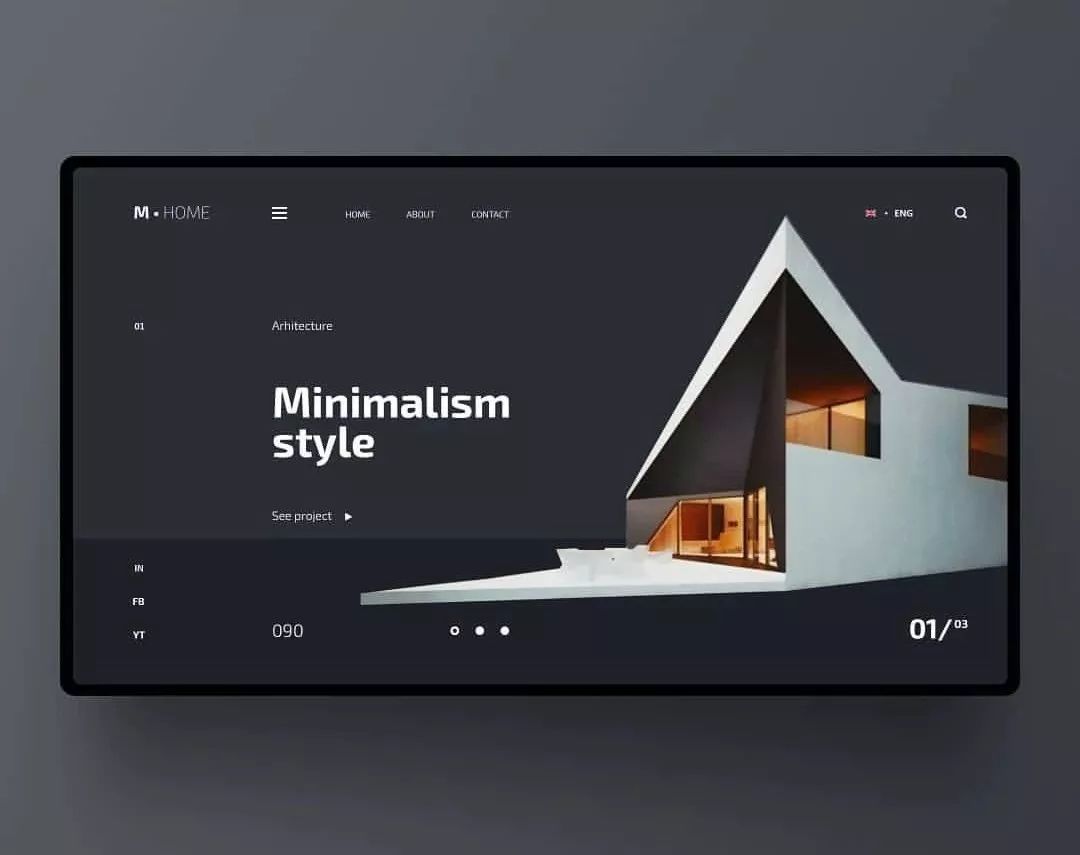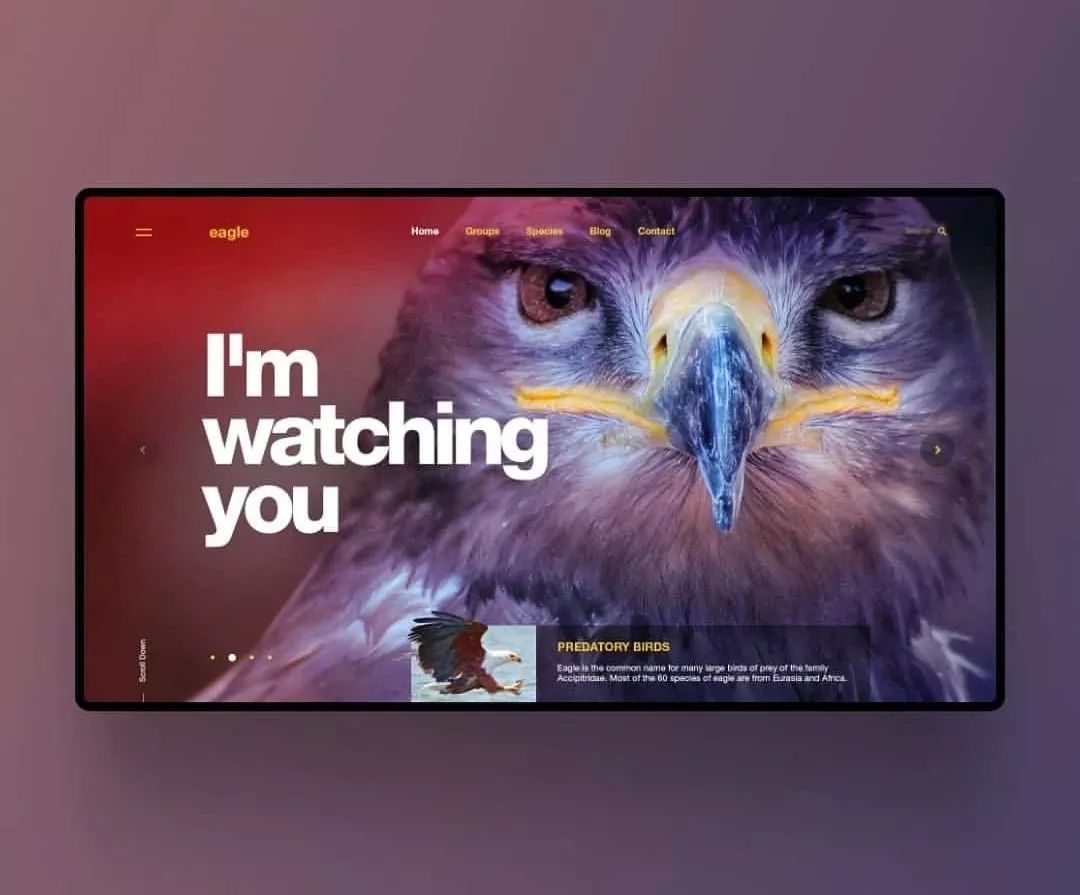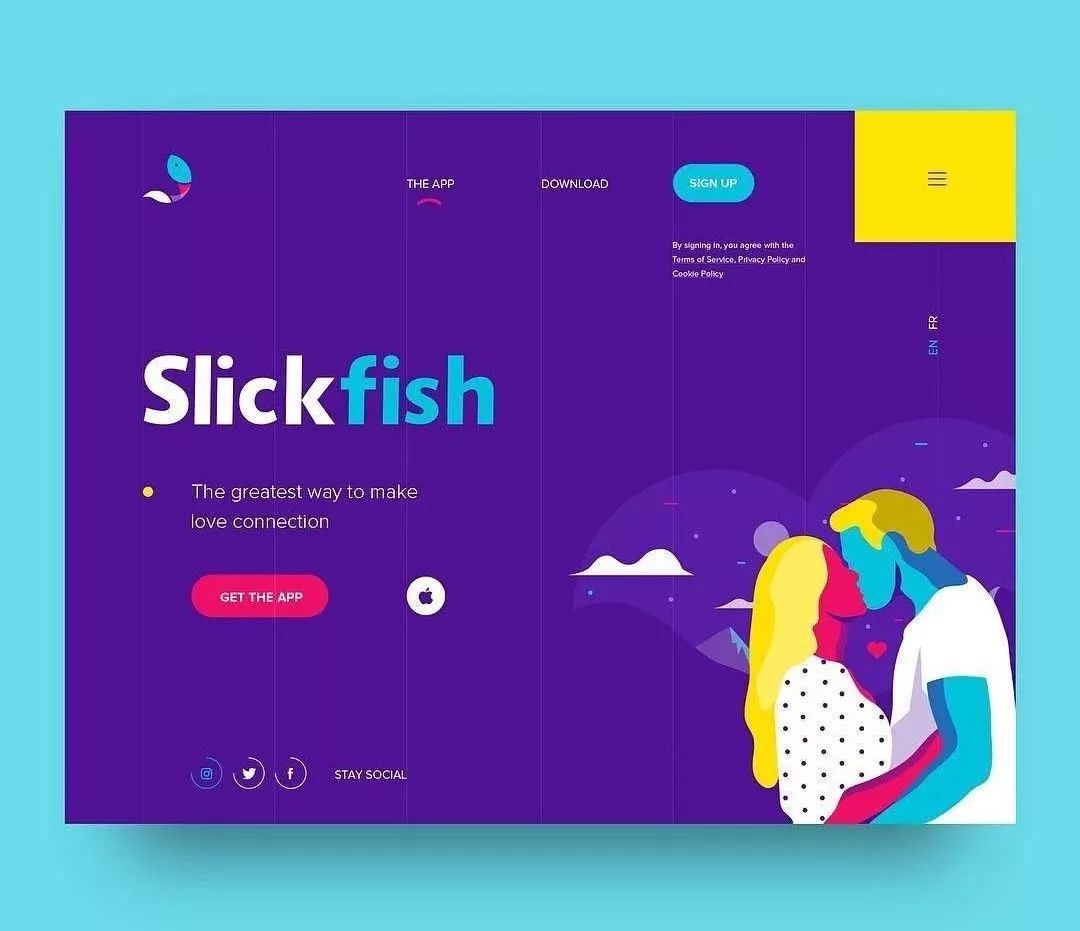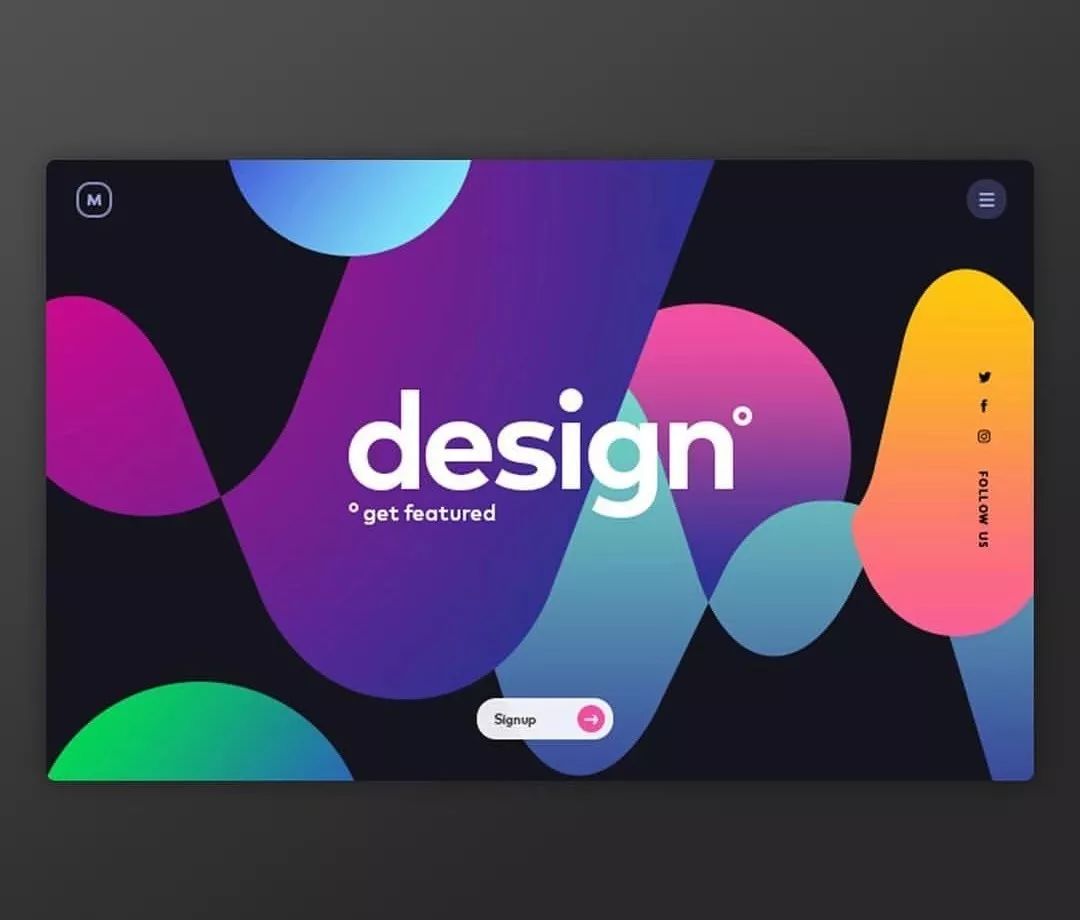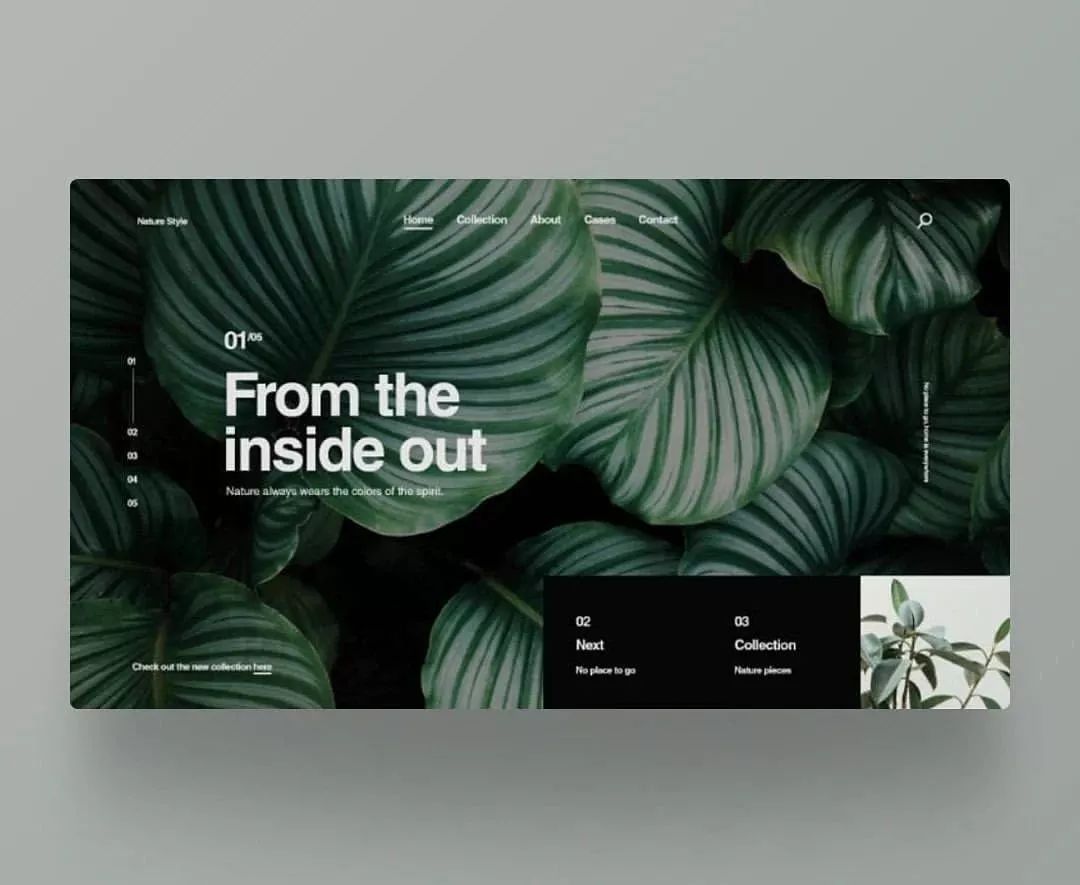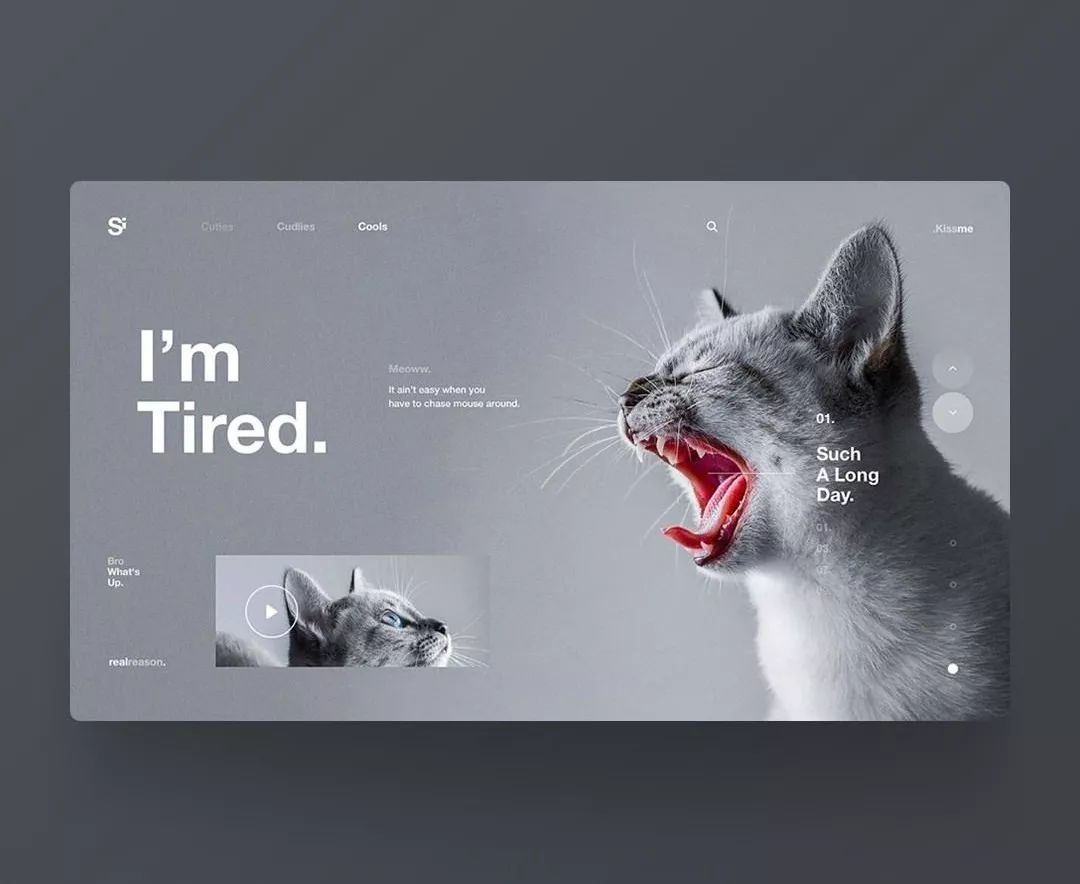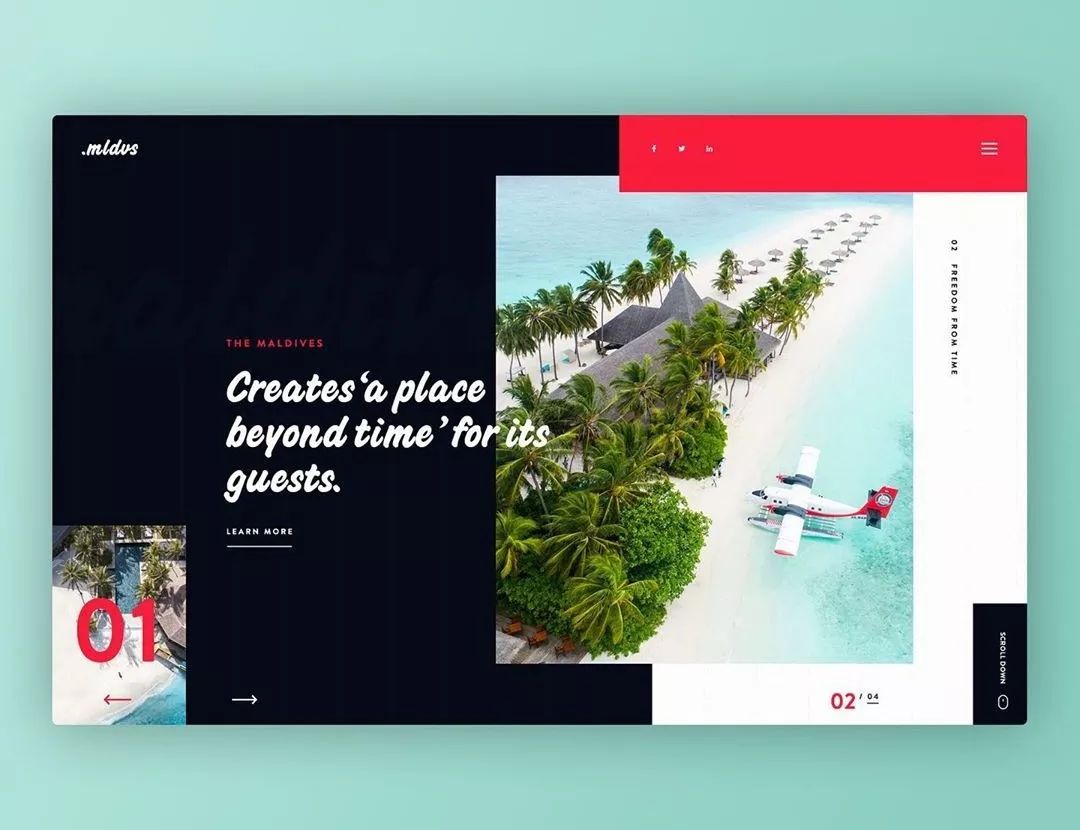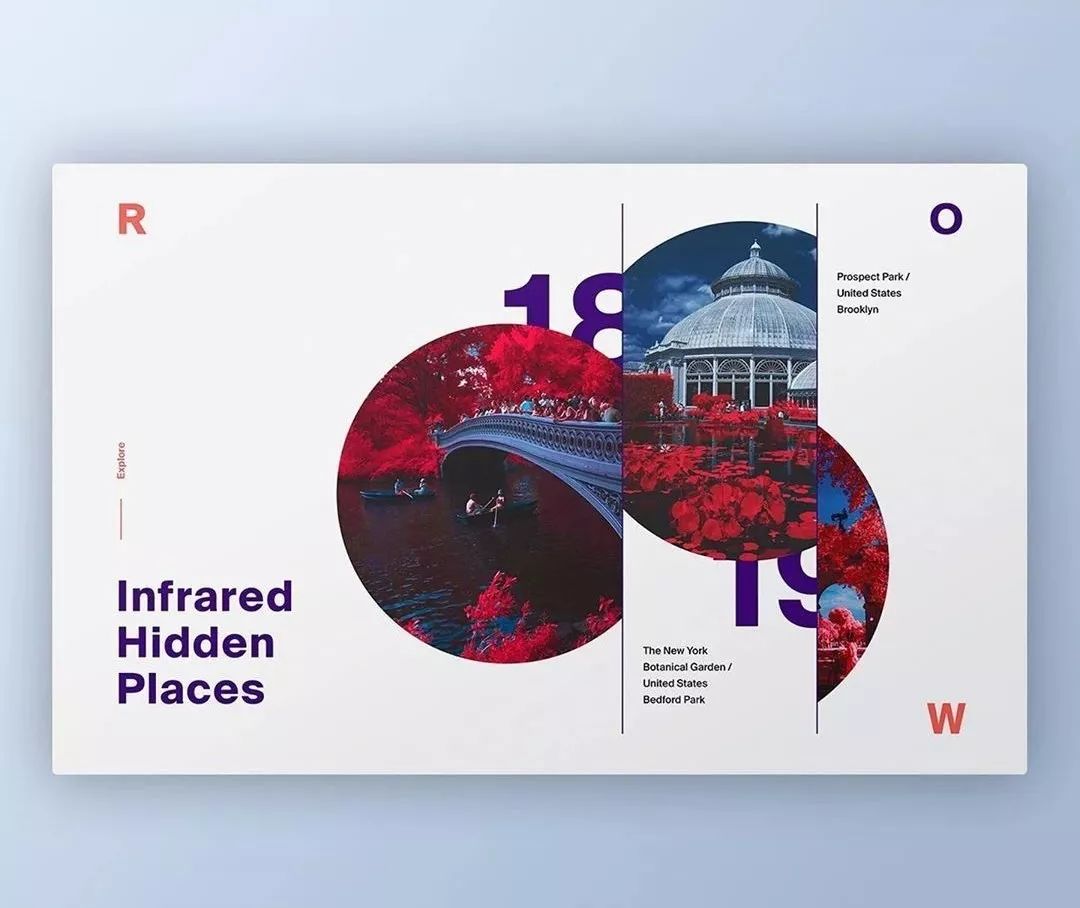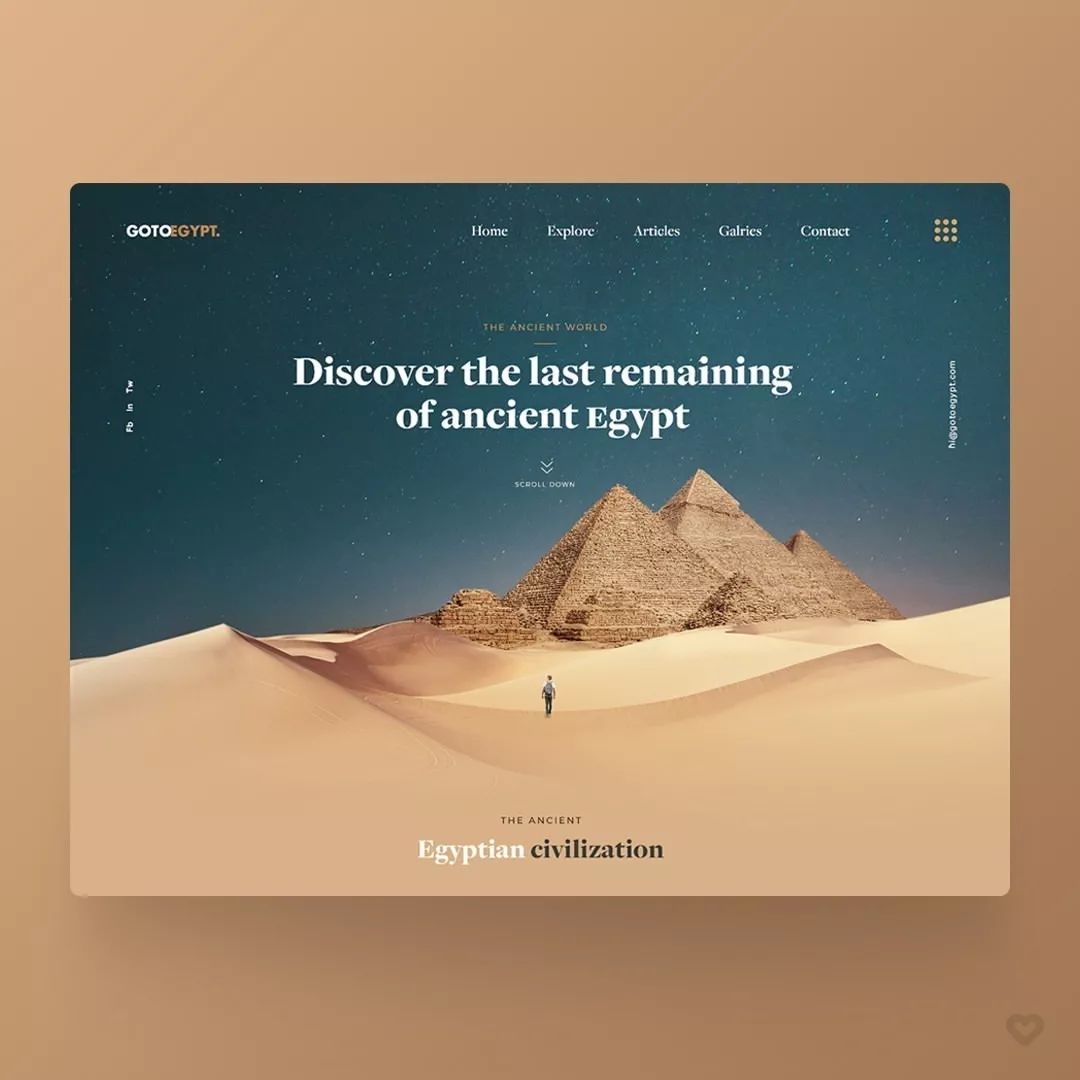
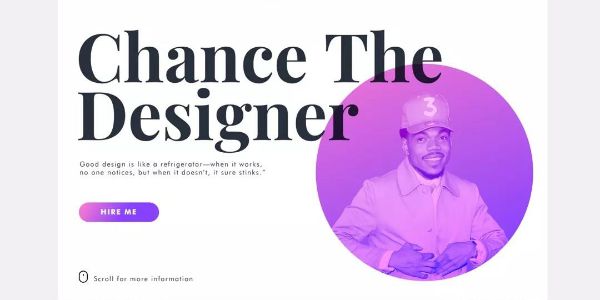
跟着网页轮播图学设计
轮播图或者说banner图是用户在网站首页最先看到的画面,所以品牌方和设计师都会比较重视,再加上网页设计自带互联网属性,又是RGB颜色模式,所以有很多优秀的作品,是学习排版、构图、形式、配色的好对象,以下便是葱爷最新收集的一波banner图设计作品,来看看它们分别有哪些设计技巧值得我们学习。
▲用斜色块横跨背景,然后把主体压在色块上是一种很经典的设计形式,能够有效增强视觉冲击。
▲在灰黑的背景上搭配以白色为主、暖色为辅的主体元素。
▲把特写人物或动物五官的图片作为画面主体,全貌图则缩小作为点缀即可,背景尽量简单、模糊一点,这种形式具有很强的吸引力和感染力,但对图片质量要求比较高。
▲把具有重复元素的图片平铺当成背景,如草丛、树丛、花丛、森林、沙滩等等,通常会有不错的效果。
▲低饱和度深蓝色搭配香槟金,字体选用衬线体,老高级了。
▲去底的大图与不去底的小图形成内容上的呼应,既能增强对比,又能加强画面的整体性。
▲大面积的紫色与小面积蓝色、白色、黄色、玫红色搭在一起,会显得比较时尚、年轻。▲把同类型的2-3张图片分别嵌入到大小相同的圆内,然后把图片交叉的部分裁成直边,错位组合,并把图片与图片交接处用直线隔开。此形式给人的感觉既统一又具有变化。
▲在黑色背景中搭配高饱和度的渐变色块,色块的布局要有大小和疏密对比。
▲把背景等分成三份,任意相连两个色块使用近似色,另一色块使用与其对比较强的颜色(可以是色相对比、明度对比或饱和度对比),然后把主体置于形成对比关系的两个色块交汇处。另,在标题中建立文字的粗细对比会显得更精致。
▲把背景分为对比鲜明的两个色块,还是把主体置于色块交汇处,然后把图片属于相应色块的部分调成与色块同色系。
▲把标题与内文左对齐,然后用短线把二者隔开,标题与内文距离短线的高度控制在内文文字高度的2-4倍为最佳。
▲把去底图片嵌入圆形色块中,并把图片颜色与色块颜色统一,在排版时,可以把部分标题文字叠加在色块上。
▲把照片叠印在背景色块中,并使用比较低的透明度,可以使画面更有细节和空间感。
▲把文字或图形作为产品图片的背景,可以增加设计感。
▲当主体位于横版画面的中间时,把主要信息集中排在一侧,另一侧可以保留大量的留白,只需把标题横跨左右两边,并在留白的一侧尾端添加一点小元素就能保持版面的平衡。
▲还是横版,还是主体位于中央,此时两次的元素可以集中在一个矩形内排版,并严格对齐,而主体元素可以适当打破矩形,这样做可以做到既平衡统一,又有对比和变化。▲用几何色块以及图片排版时,色块大小不要太平均,而是要有大小对比,(把图片也看作色块。)
▲用描边字做底,然后在其基础上排列文字,把主体元素的另一个形态作为背景。
▲用几何形摄影图片与去底的辅助元素(树枝、水草、花草等等)组合在一起,一简一繁、一刚一柔形成强烈的对比,具有不错的视觉效果。
▲把场景中的元素抠出来一点叠在文字上方,可以加强图片与文字的关联,以及画面的空间感。